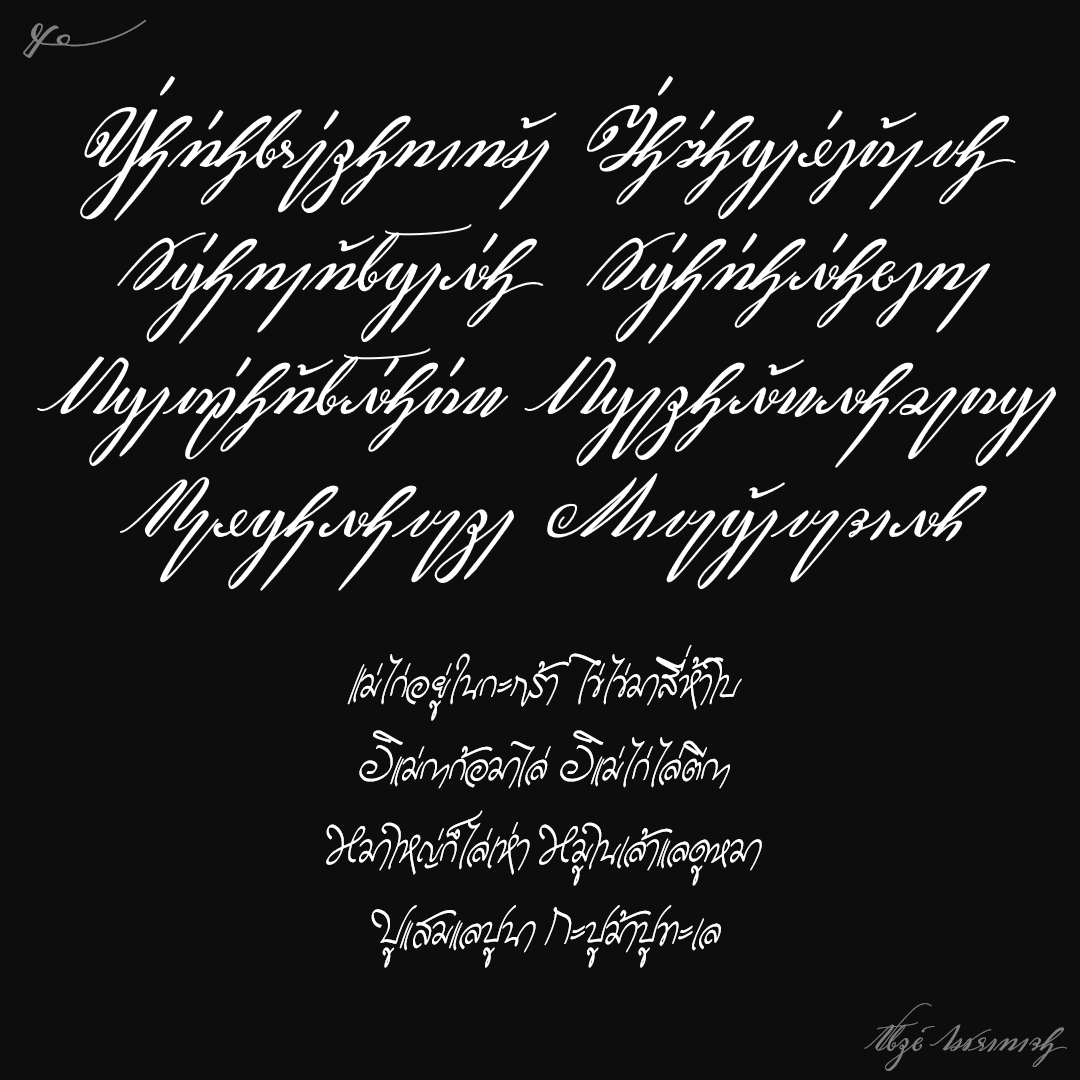
ชื่อฟอนต์ : อริยกะไท
ฟอนต์อักษรอริยกะตัวเขียน ใช้ได้ทั้งภาษาไทย และภาษาบาลี ..ต่างจากอักษรปัจจุบันทั้งรูปอักษร วิธีพิมพ์ แนะนำให้ดูคู่มือก่อนใช้งาน
แถม.. ฟอนต์อริยกะปาฬิ(AriyakaPL) สำหรับบาลีตัวเขียนโดยเฉพาะ..พิมพ์แบบไทยพินทุ